photoshop中级教程!如何制作一个好看的粉笔字效果?
1、创建一个新的1000 x 1000 px文档,新图层并使用#62c3c9进行填充。
2. 如何使用钢笔工具创建语音泡沫形状
选择钢笔工具(P) 并绘制语音气泡形状。 要创建曲线,请单击并按住鼠标并拖动。 将平滑锚点转到尖点,请在锚点上按住Alt键单击。
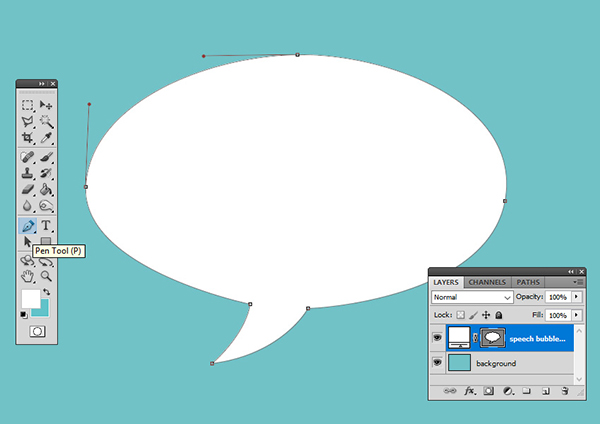
3. 创建黑板纹理
步骤1
将前景颜色设置为#1a1a1a,将背景颜色设置为#ffffff。
创建一个新图层并将其命名为Chalkboard Texture,填充颜色 #1a1a1a。
步骤2、转到滤镜>杂色>添加杂色,设置数量为50%。
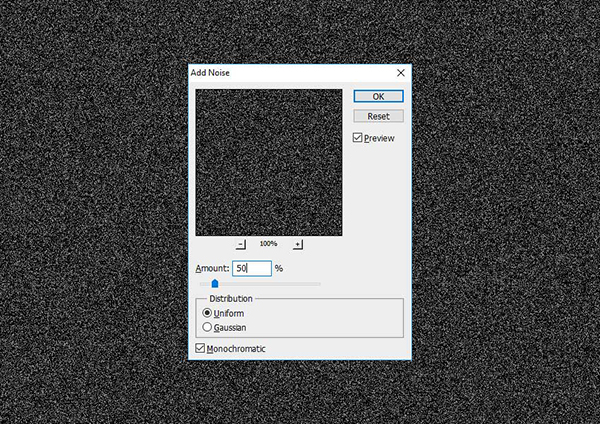
步骤3、转到滤镜>模糊>动感模糊,将角度设置为50,将距离设置为19像素。
步骤4、转到图层>新建调整图层>色阶,并使用下面这些参数设置。
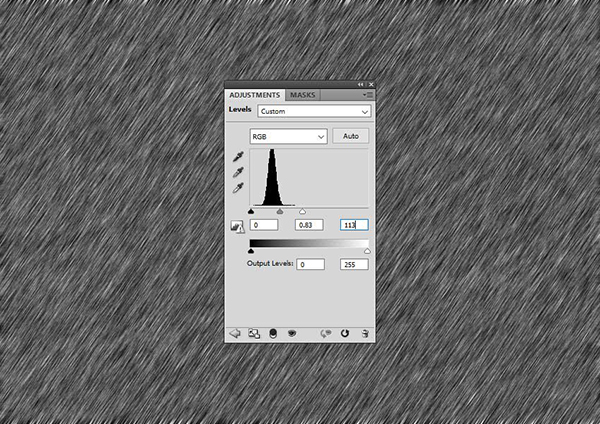
步骤5、选择“ Chalkboard Texture”图层和“ 色阶”调整图层,单击鼠标右键,然后选择“ 合并图层”。重命名新图层为“Chalkboard Texture”。
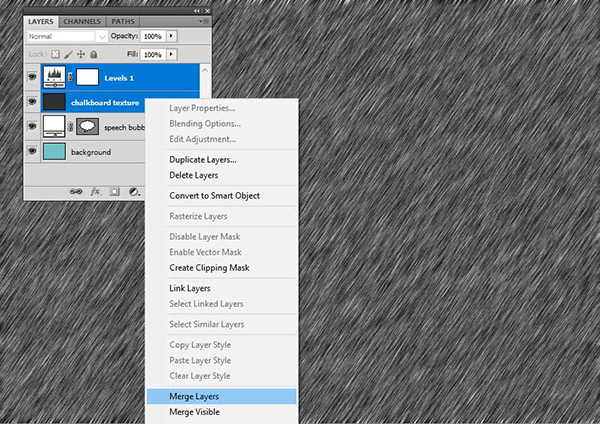
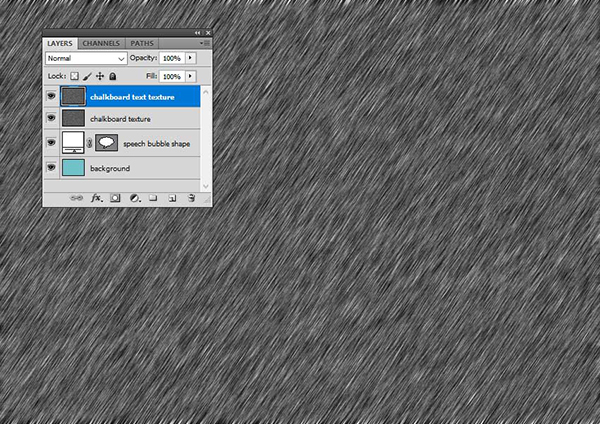
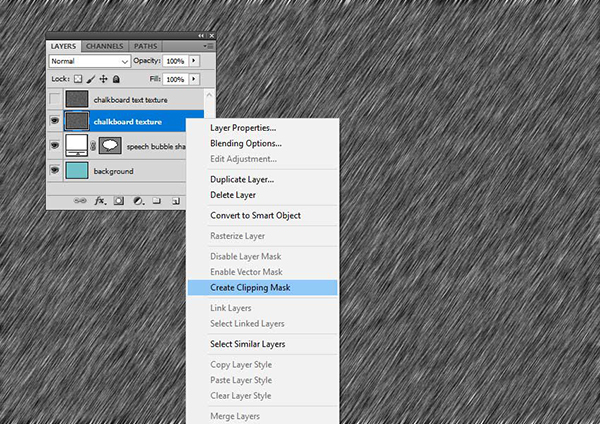
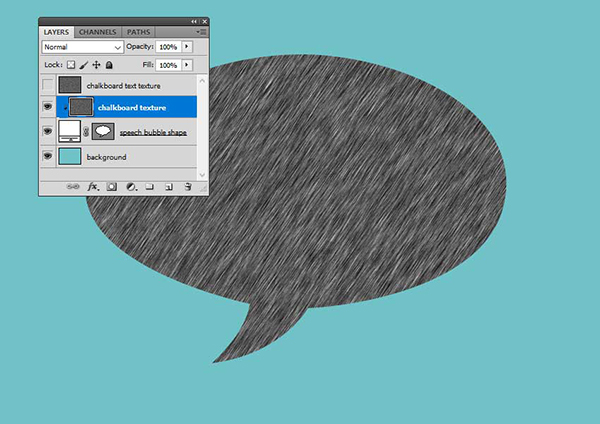
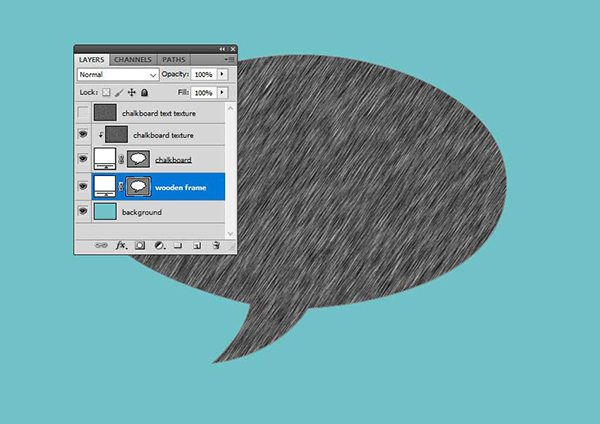
右键单击图层,然后选择“ 转换为智能对象”。
5. 创建木质纹理
步骤1
按Control-N创建一个新图层,将图层命名为Wooden Texture,填充颜色#1a1a1a。
步骤2、转到滤镜>渲染>光纤以创建木材纹理。
步骤3、右键单击 “ Wooden Texture”图层,然后选择“ 创建剪贴蒙版”。
步骤4、选择“ Wooden Frame”和“ Wooden Texture”图层,然后将它们移动到所有其他图层上方。
步骤5、给图层Wooden Frame添加以下样式:
投影 (颜色#000000)
内阴影 (颜色 #000000)
斜面和浮雕 (颜色#ffffff和 #000000)
颜色叠加 (颜色#c86800)
6. 使用木制框架创建黑板
将此图层样式添加到Chalkboard图层:
投影 (颜色 #000000)
内阴影 (颜色 #000000)
内发光 (颜色 #ffffff)
颜色叠加 (颜色 #393838)
7. 添加粉笔文字效果
步骤1、输入文字“BACK TO SCHOOL”并填充白色。
步骤2、将此图层样式添加到“ BACK TO SCHOOL” 文本图层:
内阴影 (颜色 #000000)
外发光 (颜色 #ffffff)
内发光 (颜色 #000000)
中风(颜色 #000000)
步骤3、还可以使用你喜欢的颜色添加颜色叠加,混合模式正常,不透明度100%。我会用这种绿色调#d1ff6e,还可以使用你喜欢的任何颜色更改笔划的颜色。
步骤4、右键单击 “ BACK TO SCHOOL” 文本图层,然后选择“ 转换为智能对象”,将混合模式设置为滤色。
步骤5、要创建更逼真的粉笔效果,请使“ Chalkboard Text Texture”图层可见。右键单击图层,然后 为“ BACK TO SCHOOL” 文本图层选择“ 创建剪贴蒙版 ” 。同时将混合模式设置为“ 正片叠底”。
步骤、为了使颜色更加生动,让我们添加一个调整图层。右键单击调整图层,然后选择“ 创建剪贴蒙版”。
8. 添加粉笔片
步骤1、使用钢笔工具创建粉笔。
步骤2
添加此图层样式以创建逼真的粉笔:
投影 (颜色 #000000)
内阴影 (颜色 #000000)
斜面和浮雕 (颜色 #ffffff和 #000000)
颜色叠加 (#f2f2f2白色粉笔和#c1e053绿色粉笔的颜色)
ok,完成了,在本教程中,学习了如何使用滤镜和调整图层从头开始在Photoshop中创建粉笔效果,快去试试把。